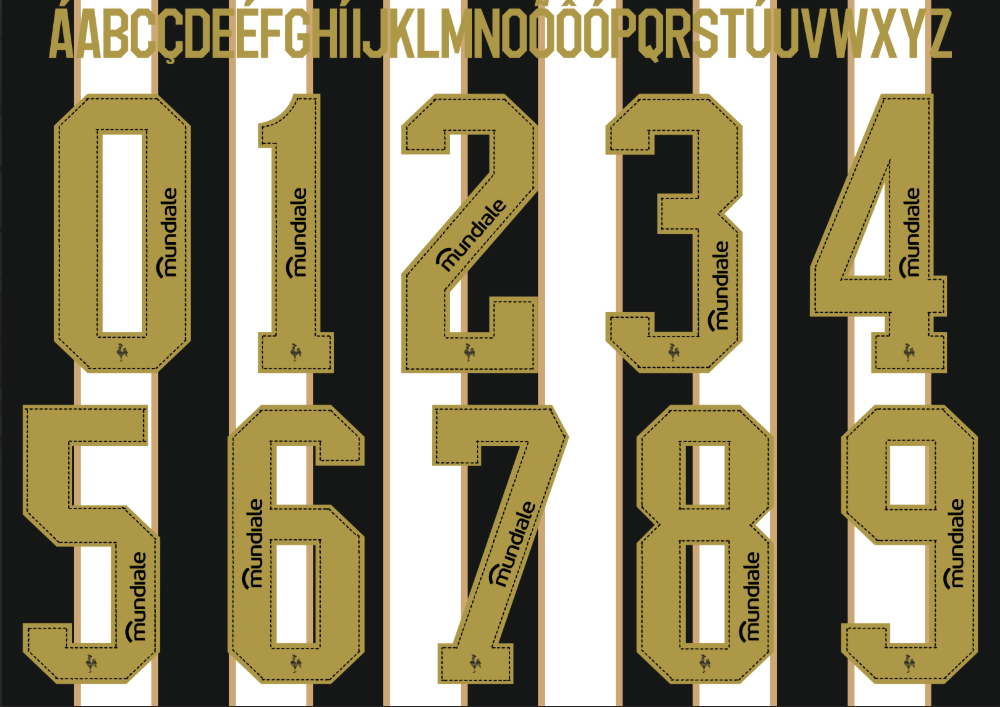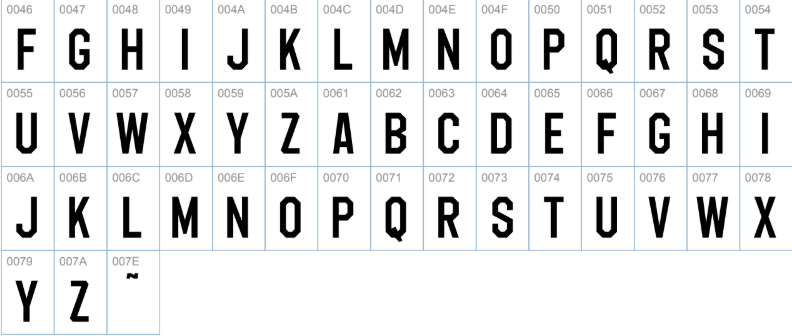
A Massa pediu e a mudança aconteceu. A temporada 2026 marca o início da era Nike no Atlético Mineiro, trazendo o icônico “Swoosh” para o manto alvinegro. A nova parceria promete elevar o nível dos uniformes com tecnologia de ponta e um design globalizado.
Com a troca de fornecedor, a tipografia também mudou completamente. Neste post, você baixa a fonte oficial exata que está sendo usada nas costas dos jogadores do Galo, pronta para suas edições e personalizações.
Estilo Visual da Tipografia
A Nike chegou ao Atlético com uma proposta visual agressiva e moderna. Diferente das fontes anteriores, a tipografia de 2026 aposta em traços mais finos e dinâmicos, garantindo leveza ao visual da camisa listrada.
Os números possuem cortes diagonais característicos da marca norte-americana, projetados para criar uma sensação de movimento. A cor (normalmente vermelha ou branca, dependendo do kit) contrasta perfeitamente com o fundo, garantindo leitura rápida e um visual impactante nas transmissões de TV e na arquibancada da Arena MRV.